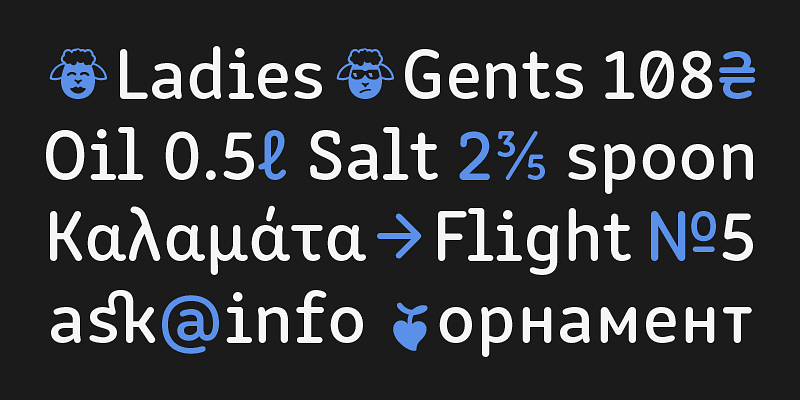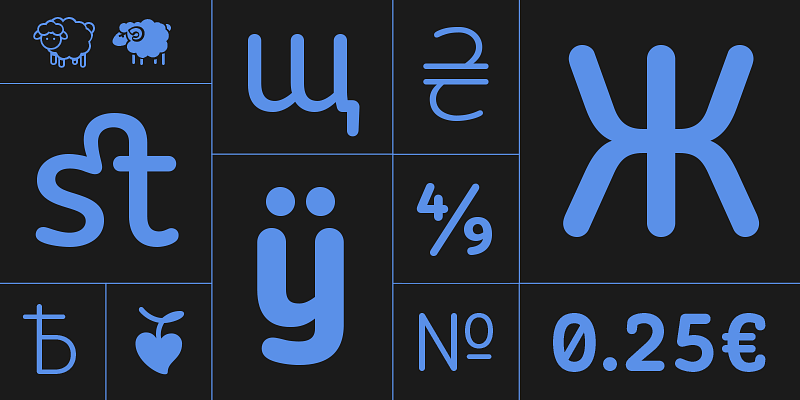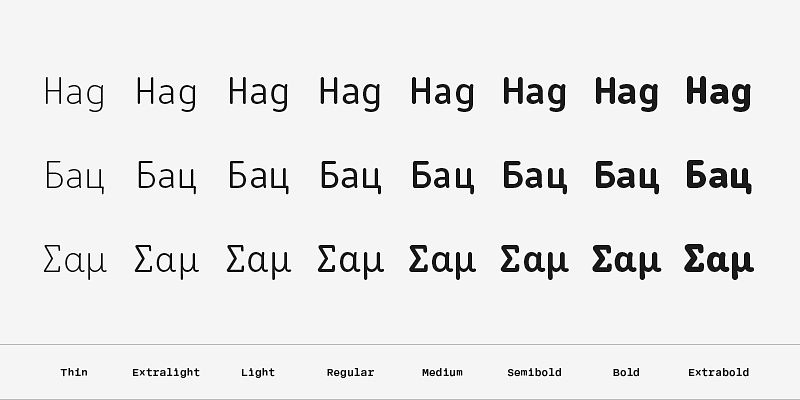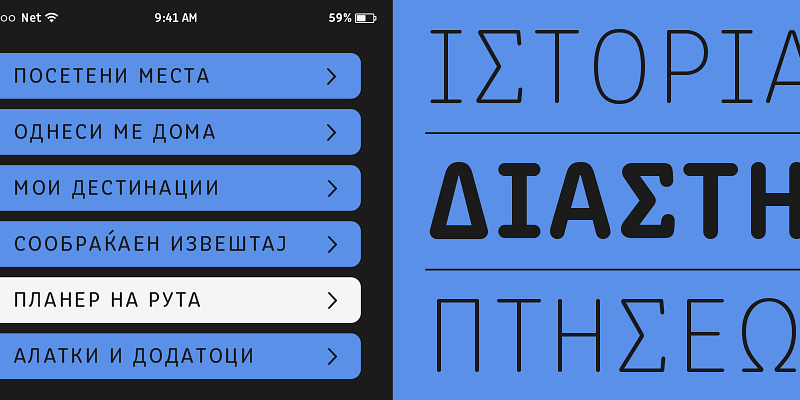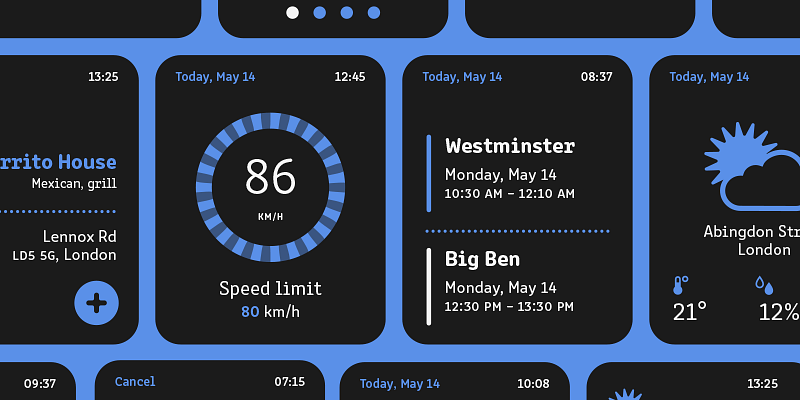
Police de caractères organique et futuriste qui rappelle les formes monospace, génétiquement moulée dans une fonte proportionnelle pour rendre la lecture confortable. Faisant écho aux prémices de l’informatique et de l’automatisation, elle est adoucie pour atténuer les angles rigides de la production mécanique.